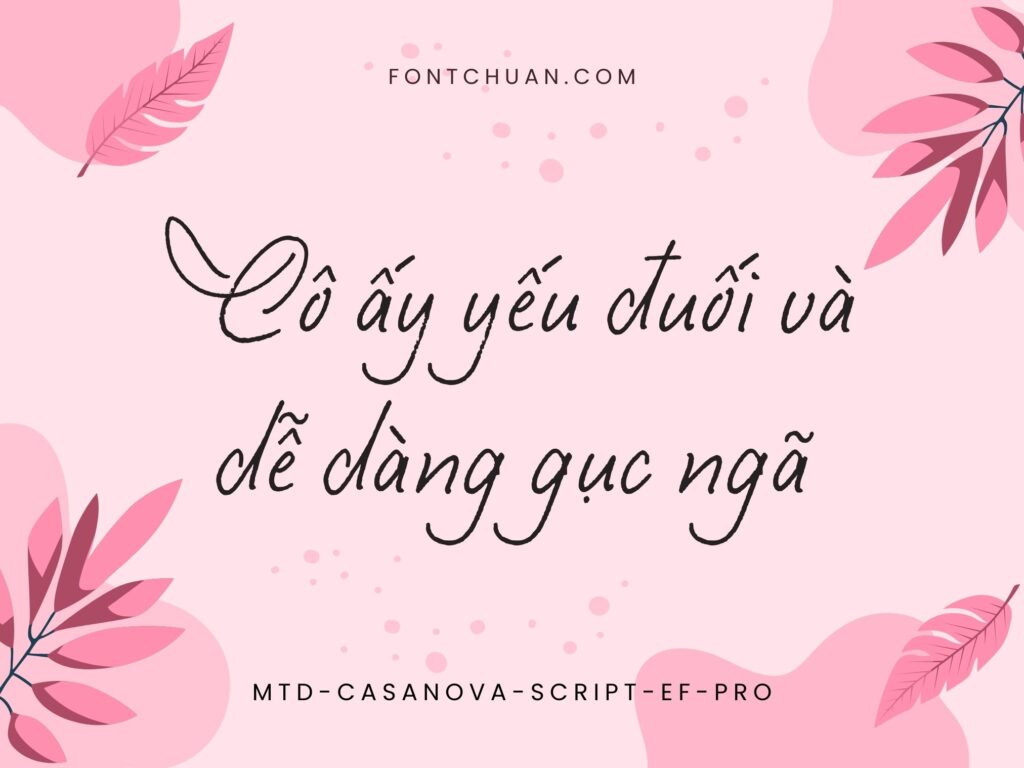
Font MTD Casanova Script Ef Pro Việt Hóa
Tác giả Font: Elsner+Flake
Font MTD Casanova Script EF Pro là một kiểu chữ viết tay thanh lịch, được thiết kế bởi Petra Beisse và đã được Việt hóa bởi Mộc Hạ. Font này hỗ trợ đầy đủ tiếng Việt cùng hơn 90 ngôn ngữ khác, mở rộng khả năng ứng dụng trong các thiết kế đa ngôn ngữ. Đây là một trong những phông chữ được cộng đồng thiết kế đánh giá cao và sử dụng trong nhiều dự án sáng tạo, đáp ứng nhu cầu đa dạng của người dùng.
MTD Casanova Script EF Pro nổi bật với các đường nét mềm mại và uyển chuyển, tạo cảm giác sang trọng và nghệ thuật. Font rất phù hợp cho các thiết kế logo, tiêu đề, bao bì sản phẩm, thiệp mời và các ấn phẩm đòi hỏi sự tinh tế và độc đáo. Các ngành nghề phù hợp bao gồm quảng cáo, giáo dục, công nghệ, thiệp cưới và ảnh cưới. Font này cũng lý tưởng cho các sự kiện như Tết, Giáng sinh, Valentine và các lễ hội khác.